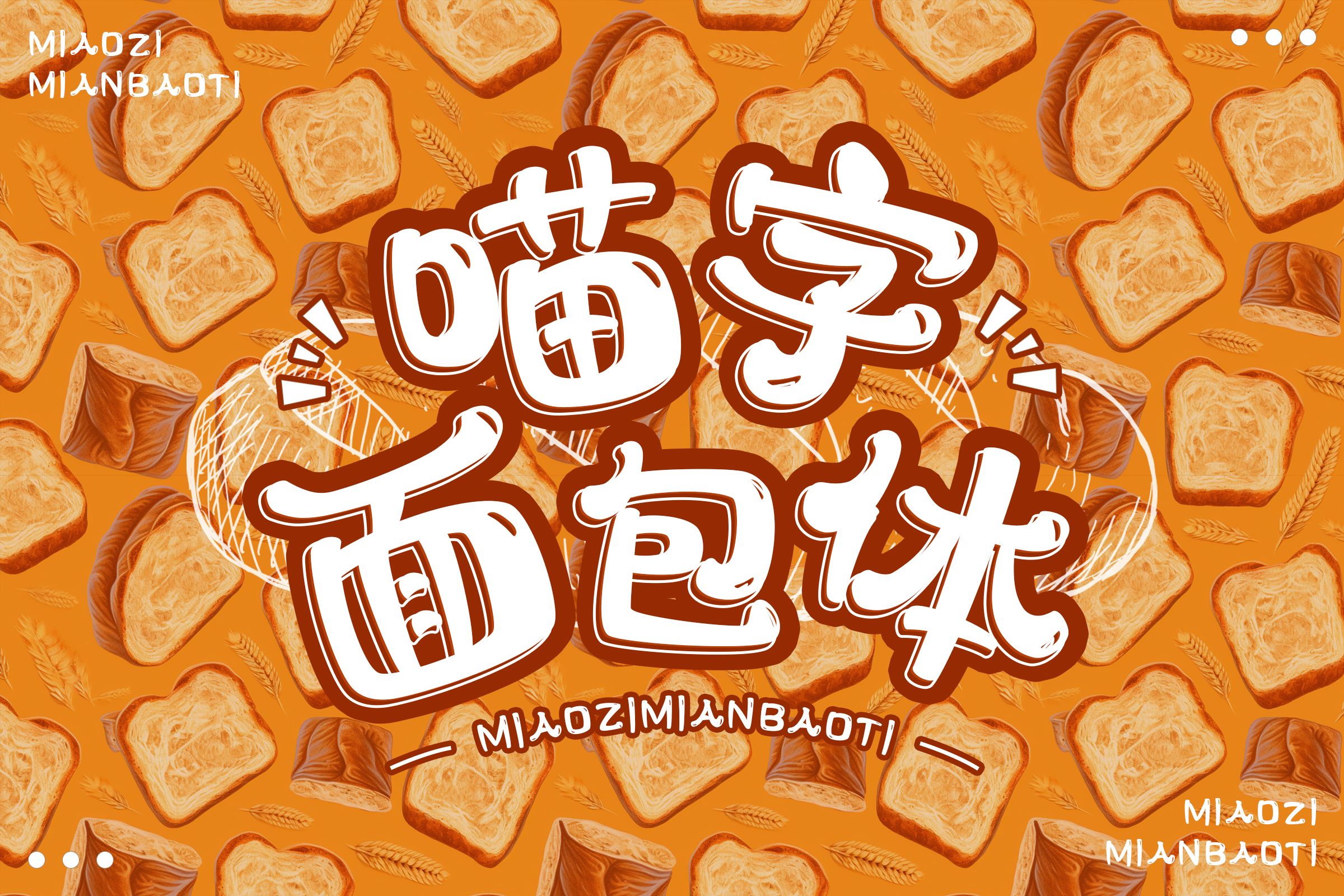
卡通风格设计必备:四款创意字库字体推荐
在设计中,字体不仅是文字的表达,更是情感和风格的传递者。特别是在卡通风格的设计中,字体的选择尤为关键。今天,我们为大家推荐四款专为卡通风格设计打造的创意字库字体,它们不仅各具特色,而且能够完美融入各种卡通场景,为你的作品增添无限趣味。
一、字恋狂漫野 鸣风
字恋狂漫野 鸣风是一款以手写感为基础的直线字体,其结构张弛有度,布白空间通透,使得整体版面更加活跃。不同字型之间有着细微的大小变化,错落有致,富有节奏感。笔画设计简洁而不呆板,钩笔画、弯钩笔画进行了去钩处理,部分笔画运用“断开”特点,使得整体风格更加独特。这款字体灰度均匀,非常适合用于卡通风格的标题或标语设计。
字恋狂饼干棒简 粗体以其随性的笔画分布和结构吸引了众多设计师的目光。这款字体仿佛是由圆滚滚的饼干棒拼凑而成,充满了童趣和无厘头的乐趣。例如“圆”字,外框一笔画出并留下一个开口,整体呈现一个倒梯形,这种设计既独特又可爱,非常适合用于卡通风格的插画或海报中。
三、字恋狂丸粒简
字恋狂丸粒简的字型可爱至极,其笔画两端和转折处都进行了圆角处理,使得整体风格圆润而富有亲和力。笔画圆头圆尾,给人一种温暖而友好的感觉。这款字体非常适合用于儿童卡通节目、游戏或玩具产品的设计中,能够迅速吸引目标受众的注意力。
四、喵字面包体
喵字面包体是一款定位于食品包装的细分字库产品,整体风貌轻盈圆润,手写感较强。每个字都巧妙地添加了高光效果,凸显立体感和卡通感,使得整体设计更加生动有趣。这款字体非常适合用于食品相关的包装产品中,能够瞬间提升产品的吸引力和市场竞争力。
这四款卡通风格的字库字体各具特色,无论是手写感的字体、随性可爱的字体、圆润亲和的字体还是立体卡通字体,都能为你的设计作品增添无限创意和乐趣。选择它们,让你的卡通风格设计更加出色!